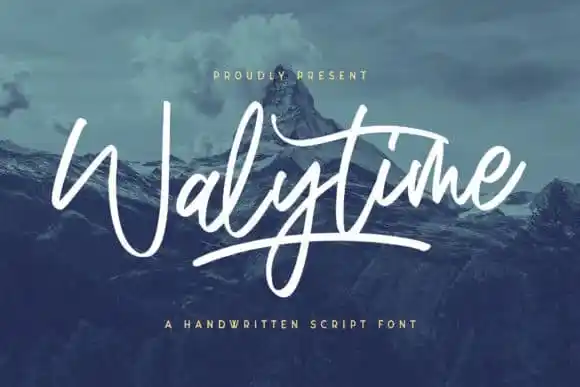
Walytime Script Font – Download Grátis
Descubra Walytime Script Font, uma escolha perfeita para designers que buscam algo romântico e elegante na categoria de fontes script. Inspirado no estilo de traçar com pincel, este tipo de letra foi criada usando ferramentas manuais simples, mas levemente refinadas. Crie um charme único em seu design, seja para anúncios de casamento, arte elegante de estação ou postagens sociais chamativas. Construída por designers do 99designs e compartilhada pela StringLabs, essa font é perfeita para um uso casual e eterno. Se apaixone pelo seu estilo versátil e utilize-o para criar anúncios de casamento incrivelmente bonitos, arte de estação sofisticada ou postagens sociais que chamem a atenção. Junte-se à legião de designers que encontraram em Walytime Script Font o tipo perfeito para seus projetos mais criativos. Transforme seu trabalho em um verdadeiro obra-prima com essa font excepcionalmente versátil e única.